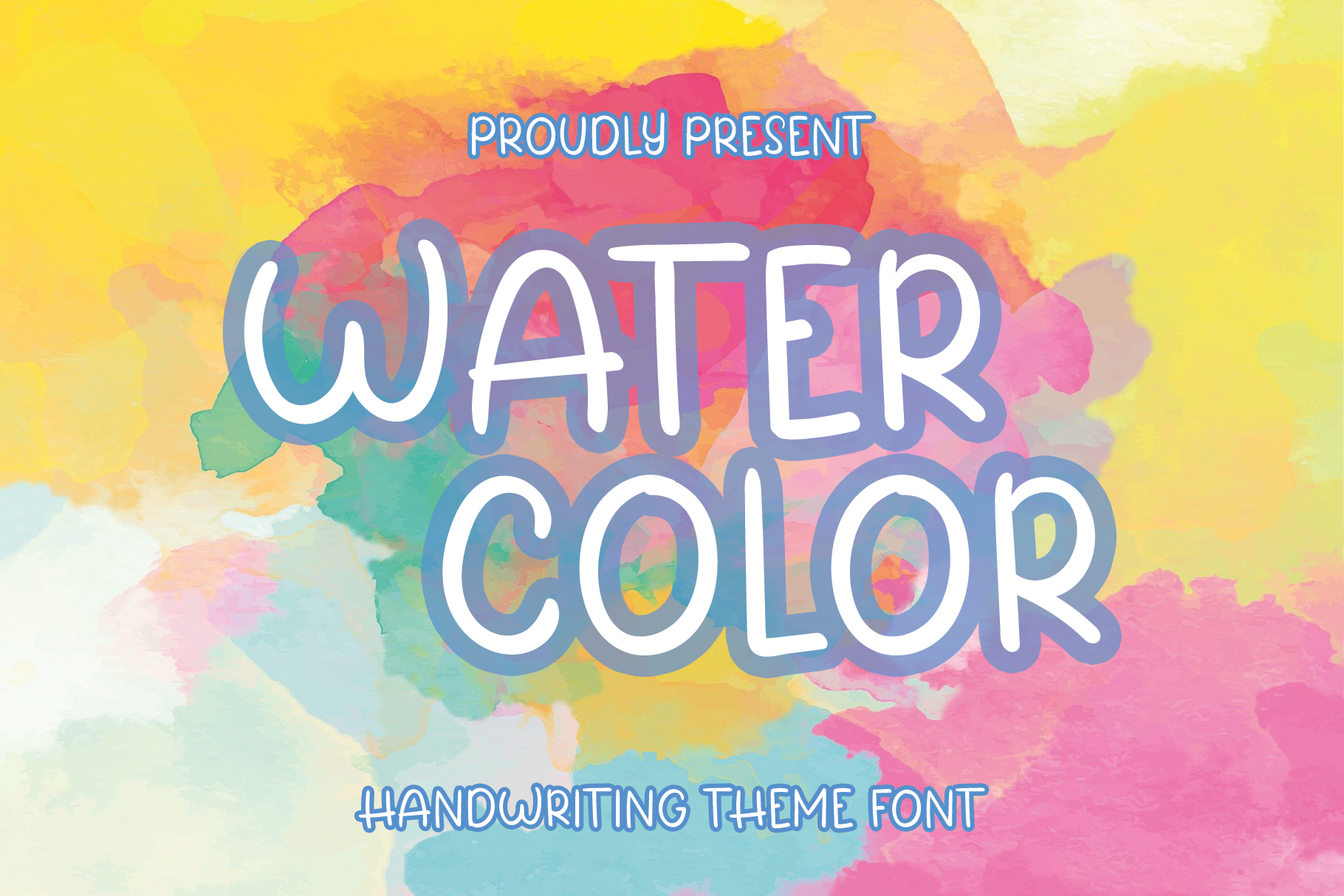
Water Color Font – Fonte Grátis
Water Color Font
Esta é uma fonte script aparentemente criada pelo designer el hotcig, que traz consigo um toque casual e neutro, mas ainda assim com um estilo suavizado e bem definido para utilização nos displays digitais ou impressos. Ela se destaca por sua capacidade de ser aplicada em qualquer projeto, independente do assunto ou contexto, transformando seu design num elemento único e destacado. Este é um excelente adicional à sua coleção de fontes, pois acredita-se que possa potencialmente revolucionar qualquer criação para a qual seja aplicada. Seja você um designer gráfico, uma agência de marketing ou até mesmo alguém interessado em design pessoal, essa fonte “Water Color Font” oferece o que há de melhor em termos de estilo casual e elegante. Ela é perfeitamente adaptável tanto para textos quanto para gráficos e elementos visuais, tornando-a uma excelente escolha para quem busca um toque único e criativo em suas produções.
Designer: el hotcig